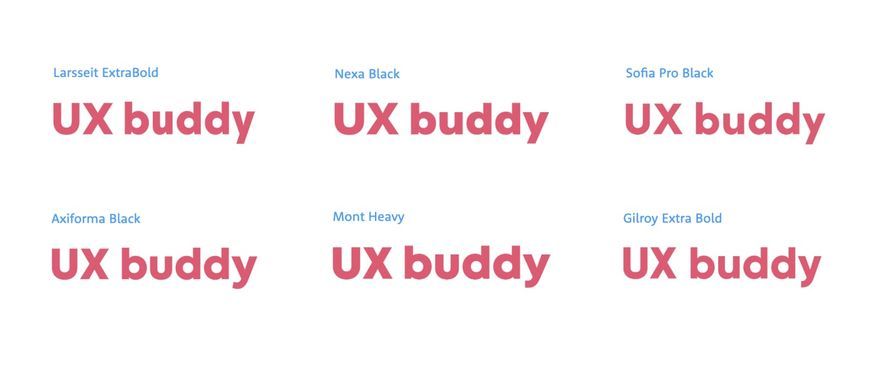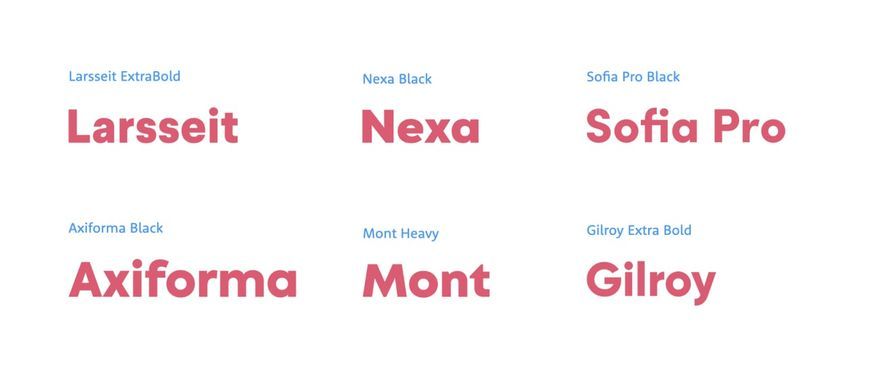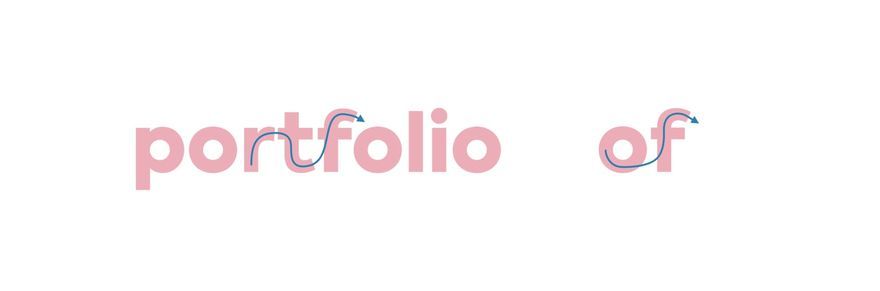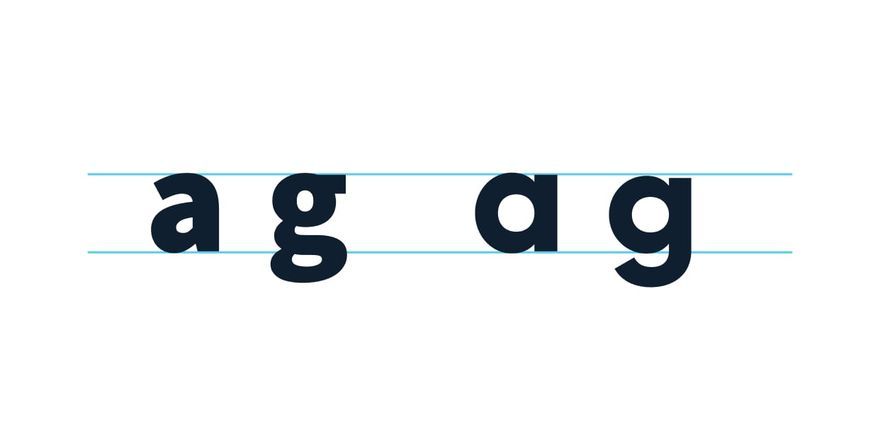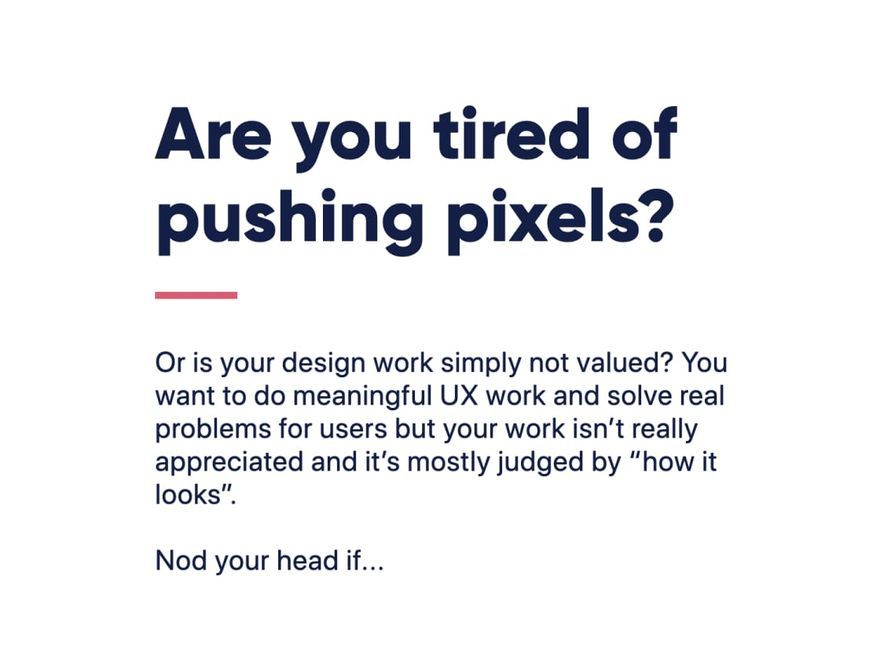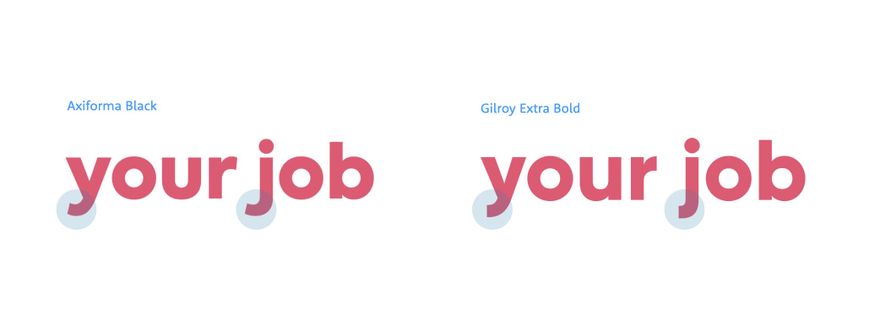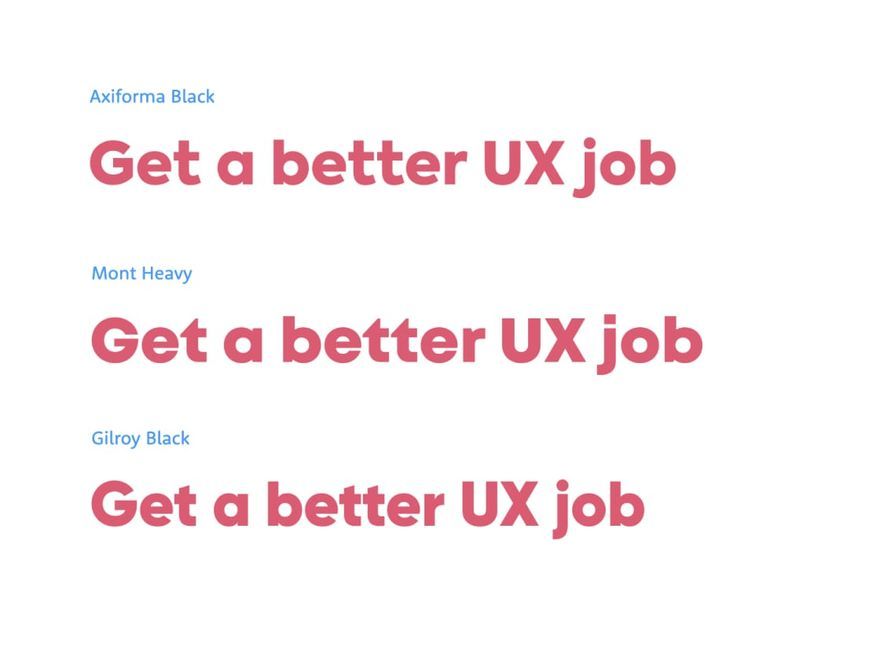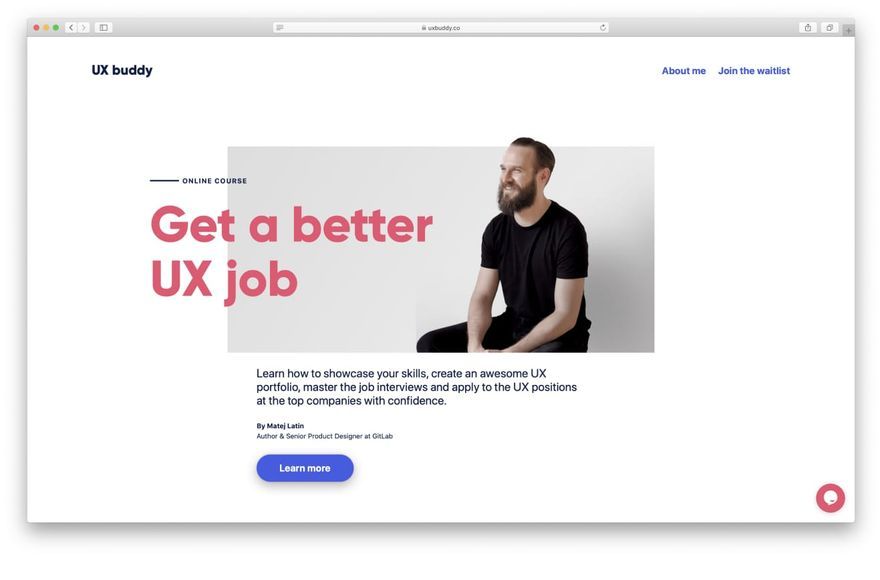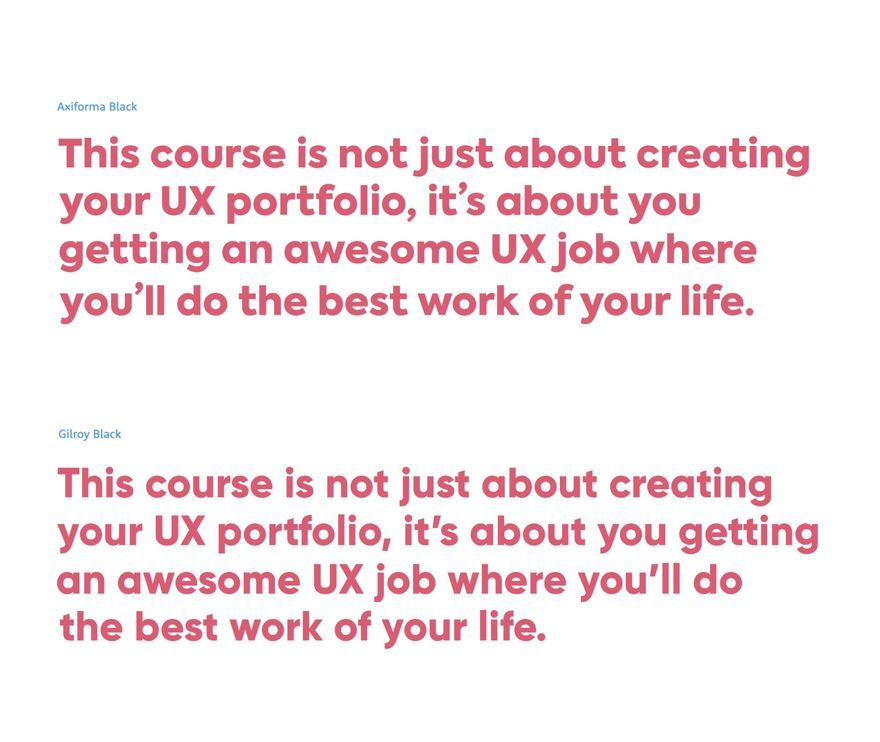
Как подобрать шрифт для дизайн проекта
Недавно я получил email от дизайнера по имени Джаред. Он прошел уроки типографики, которые я предлагаю в рамках бесплатного курса, и был очень благодарен за него. Он сказал, что многому научился, но у него возник один важный вопрос: как выбрать шрифт для своего проекта?
Он рассказал мне, что работает в дизайн агентстве, и постоянно выбирает шрифты для сайтов, над которыми они работают. Это очень расстраивает его, так как он не изучал дизайн и типографику, поэтому в основном он руководствуется своим «внутренним чутьем». Или он копирует шрифты с сайтов, которые ему нравятся. Он знает о своих проблемах с выбором оригинальных шрифтов, и его разочарование растет с каждым днем. И он не одинок.
С тех пор как в 2017 году я запустил свой бесплатный курс по веб-типографике, я, как правило, получаю пару подобных писем каждый месяц. Я написал о выборе шрифтов подробнее в моей книге о веб-типографике, где объяснил свой процесс на конкретном примере. Но не все купят книгу, поэтому я решил еще раз показать свой процесс подбора шрифтов. На этот раз с другим примером – новым личным проектом, над которым я недавно начал работать.
UX Buddy
UX Buddy будет онлайн-курсом для UX и продуктовых дизайнеров, которые хотят сделать следующий шаг в своей карьере. Мне пришлось сменить много работ, прежде чем я нашел ту, где занимаюсь тем, что нравится и что хорошо получается. Поэтому я хочу поделиться своим опытом и помочь дизайнерам в поисках лучшей UX-должности.
Я работаю в GitLab, где мы назначаем UX buddy (UX-приятеля) к дизайнерам, недавно присоединившимся к команде, чтобы помочь им влиться в рабочий процесс (UX-приятель – просто дизайнер, которому поручено помочь новичку). Первые несколько месяцев ошеломляют новых дизайнеров, поэтому UX-приятели помогают им, объясняют, как все работает, и побуждают их делать определенные вещи. С этим курсом я хочу сделать то же самое для дизайнеров, у которых застой в карьере. Но вместо того, чтобы быть их приятелем только после того, как они присоединятся к компании, я хочу помочь со всем, что предшествует этому – поиск хороших UX-компаний, написание кейс-стади, собеседование и т.д.
Готовый сайт UX Buddy
Вот откуда появилась идея курса UX Buddy и каковы его цели. Это хорошая отправная точка для определения брендинга. Поскольку курс основан на моем опыте получения работы, я хотел, чтобы брендинг отражал мою индивидуальность. Я хотел, чтобы он был минималистичным, но не лишенным своеобразия. Дружелюбным, но при этом профессиональным. Отражал суть вопроса, а не ходил вокруг да около. Затем я провел двухдневный дизайн-спринт, чтобы придумать ценностное предложение курса и контент для сайта. Целью было представить курс на одной веб-странице. Я придумал следующее:
Получите лучшую UX-должность
для заголовка страницы, и:
Этот курс не только о создании вашего UX-портфолио, но и о том, что вы получите потрясающую UX-должность, на которой создадите лучший проект в своей жизни.
для ценностного предложения. Этого было более чем достаточно, чтобы начать работать над сайтом и, соответственно, выбрать шрифт.
Выбор шрифта
Хорошо, а теперь как нам выбрать шрифт для нашего проекта? В моей книге о веб-типографике я рекомендую учитывать семь моментов. Вот три ключевых из них:
Цель сайта и его контент
В моем случае цель состоит в том, чтобы представить новый курс и себя, как заслуживающего доверия специалиста, способного преподавать. Веб-сайт не предназначен для чтения длинных статей, он должен быстро привлечь внимание посетителей.
Основной текст или заголовки
Мы выбираем шрифт для основного текста или для заголовков? Поскольку цель состоит в том, чтобы завлечь посетителей, я хотел сосредоточиться на выборе правильного шрифта для заголовков.
Текст
Чтение текстового контента сайта, для которого мы проектируем дизайн, имеет фундаментальное значение. Иначе, как выбрать шрифт для чего-то, о чем вы не знаете? Необходимо читать образцы текста в самом начале процесса проектирования. Не используйте Lorem Ipsum, если вы не можете получить образцы контента, попробуйте найти аналогичный веб-сайт и «позаимствовать» его контент, пока вы не получите образцы текста.
Для UX Buddy у меня уже было название и ценностное предложение. Поэтому я мог приступить к работе.
Что я искал
В этот момент у меня был текст для работы, я знал его цель, поэтому я сосредоточился на поиске идеального шрифта для заголовков. Это, в сочетании с брендингом, отражающим мою индивидуальность, привело меня к использованию геометрического шрифта без засечек. Моего любимого стиля. Если вы не знаете основных стилей шрифтов и как их различать, ознакомьтесь с моим руководством по распознаванию стилей шрифтов. Это самый первый шаг при выборе оригинального шрифта.
Сначала я просмотрел такие шрифты в наборах Google Fonts и Adobe Fonts, но не смог найти подходящий. Например, я знал, что хочу, чтобы шрифт имел одноэтажные строчные буквы «a» и «g».
Двухэтажные «a» и «g» слева, одноэтажные «a» и «g» справа
Мне просто нравится их простота, и я подумал, что она хорошо сочетается с минималистичным и упрощенным брендингом, к которому я стремился. Я не смог найти подобные шрифты в этих наборах, поэтому я перешел на myfonts.com. Я нашел там пару отличных вариантов: Larsseit, Nexa, Axiforma, Mont, Sofia Pro и Gilroy. Я также знал, что хочу использовать полужирный в качестве основного стиля, чтобы вызвать чувство дружелюбия. На изображении ниже, шрифты представлены в основном цвете, который я планировал использовать.